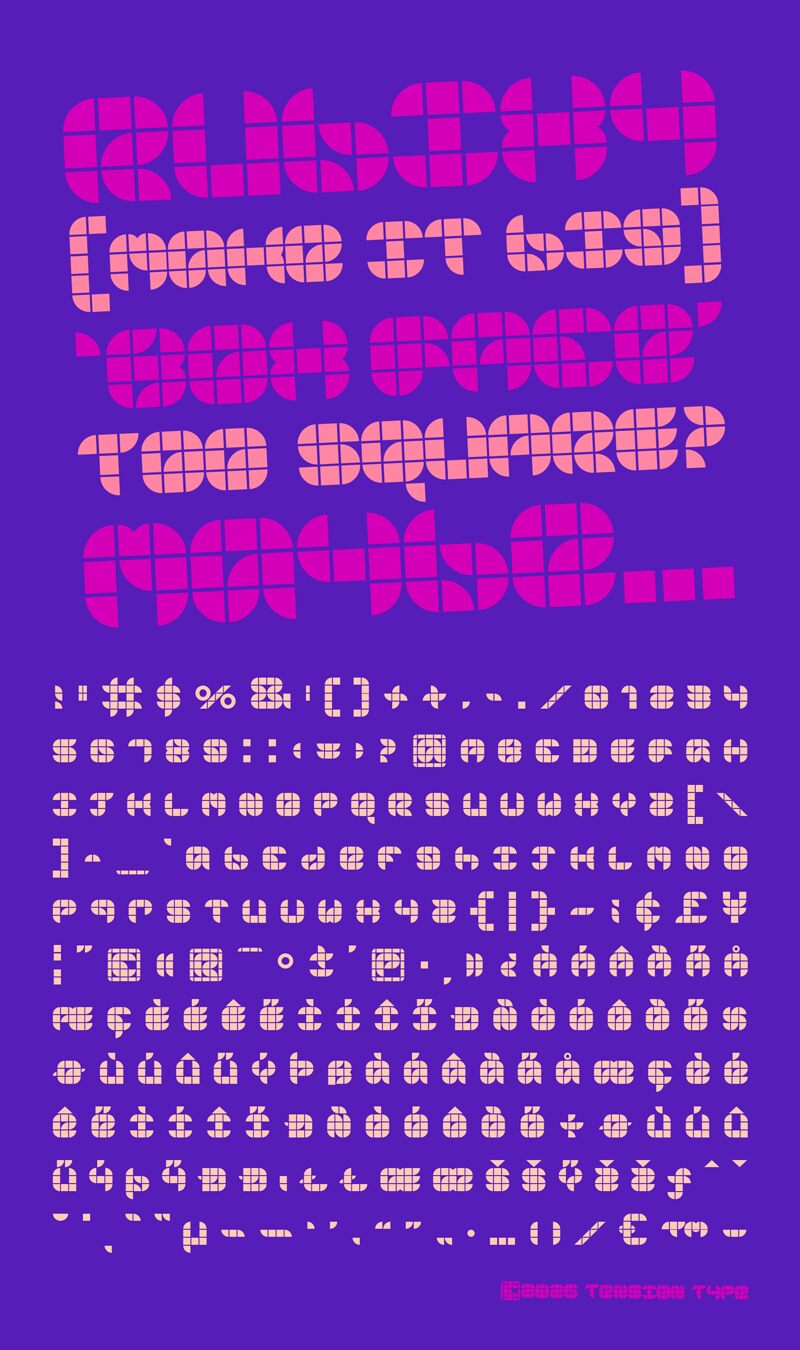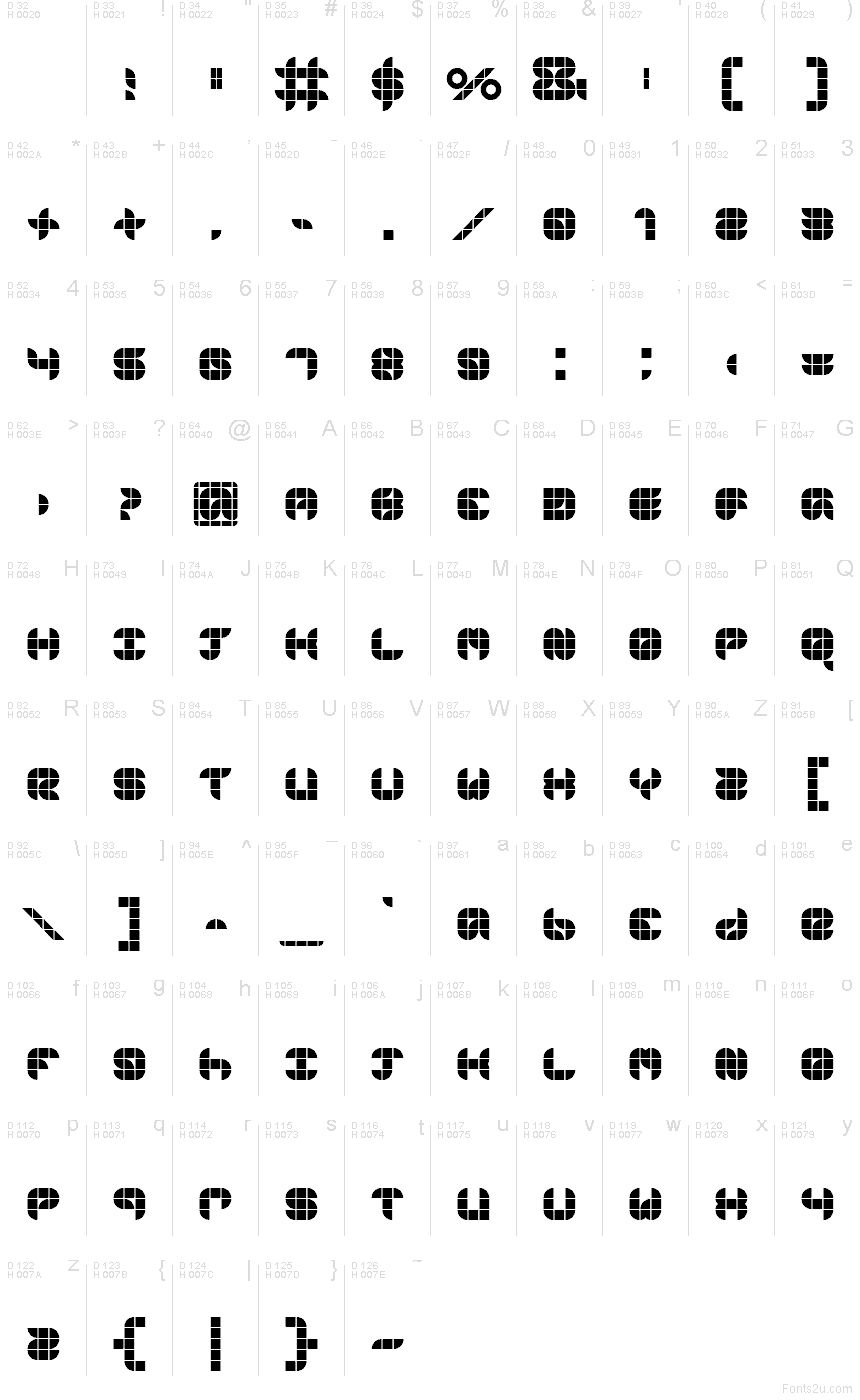
Box Face от Tension Type — это бесплатный грови-шрифт для заголовков, построенный на массивных геометрических заглавных буквах и разделенный четкой сеткой горизонтальных и вертикальных линий. Буквы напоминают модульную плитку из поп-графики конца 60-х или начала 70-х годов: скругленные углы, плотный кернинг и игривый ритм создают широкую и эффектную форму слова.
Шрифт отлично подходит для заголовков на плакатах, обложек музыкальных альбомов, эскизов логотипов, вступительных титров и упаковки, где нужно передать ретро-настроение, избегая при этом излишней сложности. Квадратная повторяемость придает коротким названиям, подписям и монограммам броский, фактурный вид, который считывается скорее как графический леттеринг, чем как нейтральный шрифт.
Box Face started as somehting for fun. I just wanted to see how many letters I could create within a minimal space. I broke a few rules along the way, but a pretty full typeface was created. But its only good at really large sizes. Display only :)